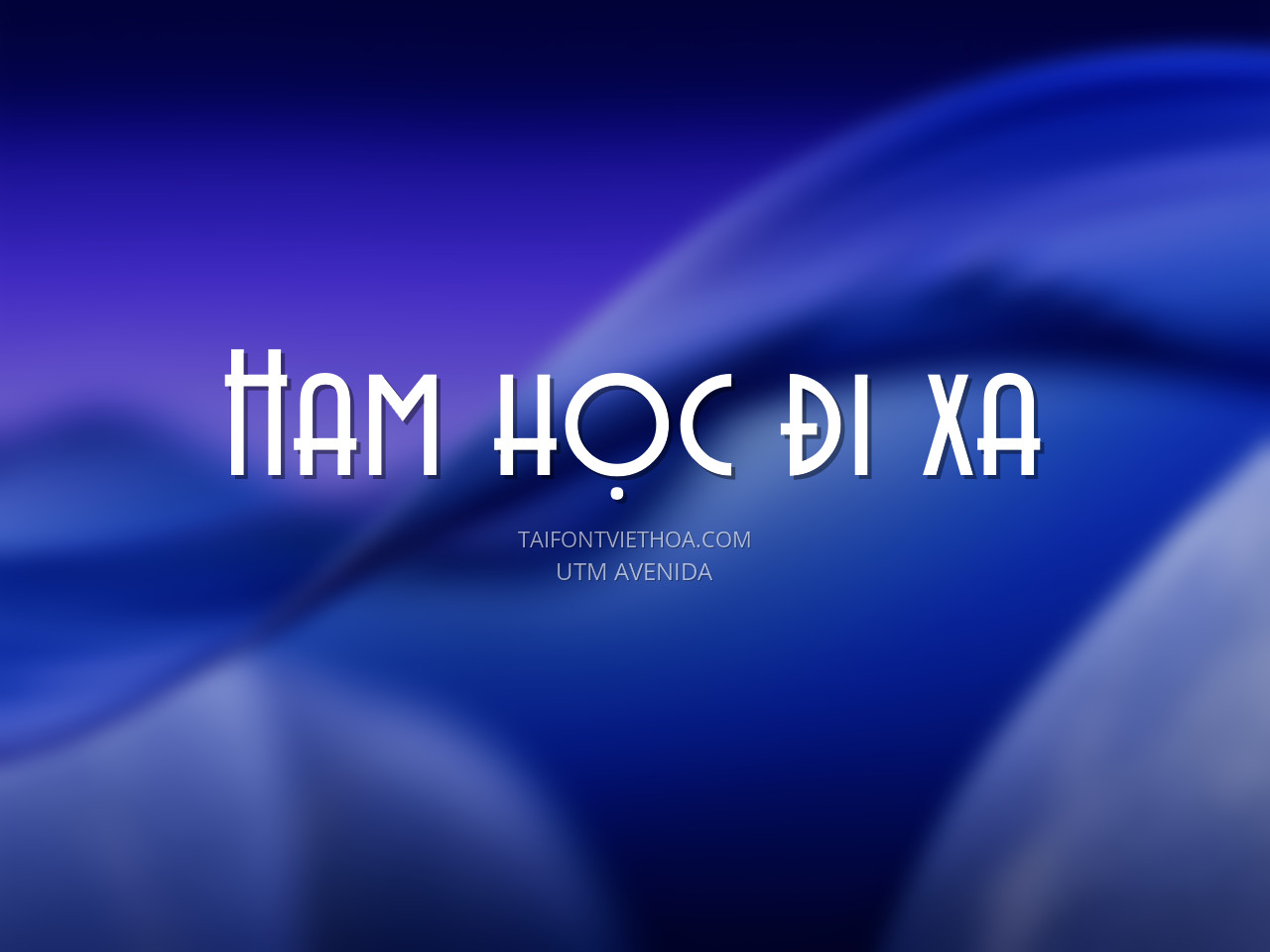
Font việt hóa UTM Avenida
Giới thiệu về font UTM Avenida
UTM Avenida là phiên bản Việt hóa của font Avenida – một kiểu chữ sans-serif hiện đại và đẳng cấp, được thiết kế bởi nhà thiết kế tài năng tại Mỹ. Font gốc nổi bật với các nét chữ dày dặn, cấu trúc cân đối và thiết kế tinh tế, phù hợp với các dự án thương hiệu và quảng cáo cao cấp. Phiên bản Việt hóa đã được phát triển để hỗ trợ đầy đủ tiếng Việt cùng hơn 200 ngôn ngữ khác, giúp mở rộng khả năng ứng dụng trong các dự án sáng tạo toàn cầu.
Đặc điểm thiết kế và ứng dụng của UTM Avenida
UTM Avenida sở hữu cấu trúc sans-serif với các nét chữ dày, vuông vức và cân đối. Font có độ dày vừa phải, thiết kế tối giản giúp tăng khả năng đọc và linh hoạt trong nhiều kích thước và môi trường hiển thị khác nhau. Font phù hợp cho các ứng dụng tiêu đề, nội dung văn bản, nhận diện thương hiệu và ấn phẩm quảng cáo.
Font thích hợp sử dụng trong thiết kế website, bao bì sản phẩm, brochure, poster, và các dự án truyền thông đa phương tiện. Các ngành nghề phù hợp gồm: công nghệ, quảng cáo, thời trang, truyền thông, giáo dục và thương mại điện tử.